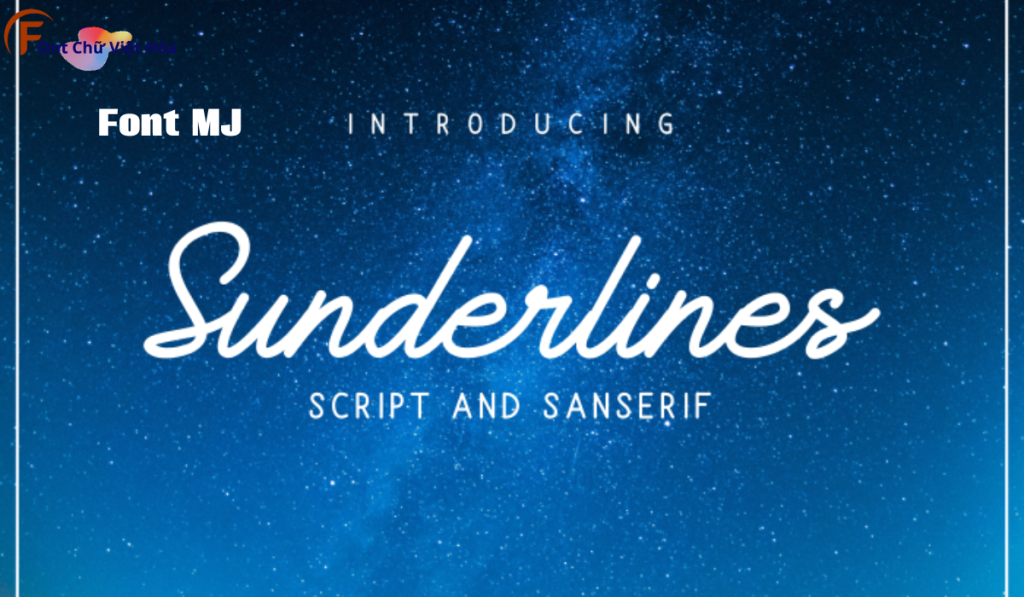
Font MJ Sunderlines Việt Hóa
Phân loại: Cá tính, Độc đáo
Kiểu chữ: Kiểu chữ có chân
Font MJ Sunderlines Việt Hóa là một font chữ có chân độc đáo, thuộc bộ font MJ. Được thiết kế với mục tiêu mang lại sự cá tính và sáng tạo, font này phù hợp cho các dự án thiết kế như logo, poster, và bao bì sản phẩm. Với các nét chữ sắc nét và độ dày đều đặn, Font MJ Sunderlines Việt Hóa không chỉ dễ đọc mà còn tạo cảm giác hiện đại và phá cách. Việc Việt hóa font giúp người dùng dễ dàng sử dụng trong các thiết kế tiếng Việt, mang lại sự tiện lợi và thẩm mỹ cao.